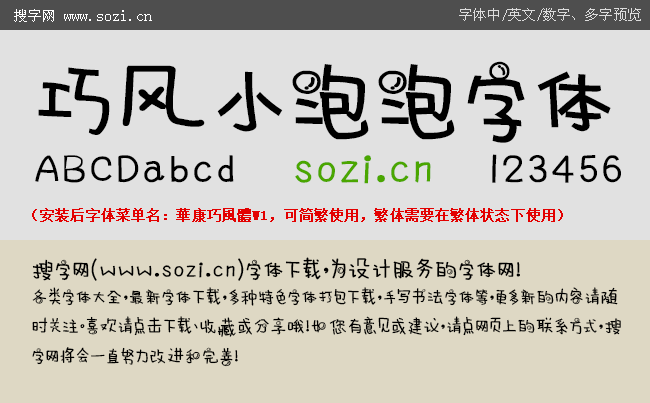
巧風(fēng)小泡泡字體
搜字網(wǎng)給大家提供一款巧風(fēng)小泡泡字體手機中文字體下載。這款手機中文字體以華康巧風(fēng)體為原形,將一些筆畫的點改成了可愛泡泡圖形,華康巧風(fēng)體是一款美術(shù)風(fēng)格的繁體字庫,摘自華康最新出品的《華康手書風(fēng)II-字得其樂》,經(jīng)過改造后更加卡通化,增加了趣味性,非常適合喜歡個性的朋友在手機上安裝使用。